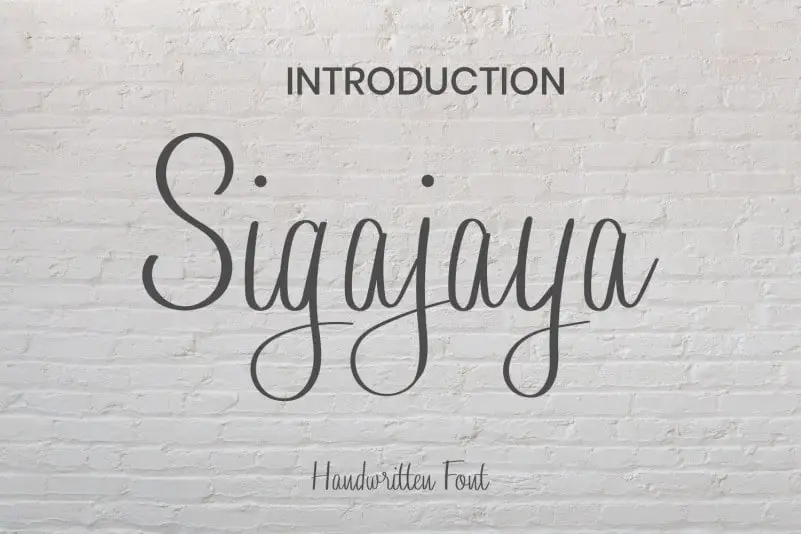
Sigajaya Handwritten Font – Download Grátis
A Sigajaya Handwritten Font é uma elegante fónta escrita a mão com um toque suave e amigável. Perfeita para aqueles desejos de criar designs alegres, essa fónta relaxada se adapta à uma ampla gama de aplicações. Seja em sua identidade visual, cartões de aniversário, postes nas redes sociais ou até mesmo seus e-mails de boas-vindas, ela é perfeitamente adaptável a esses formatos. Com sua graciosidade genuína, você pode explorar a criatividade através da design de logotipos, cartões de visita, embalagens, designs para eventos e outros. A Sigajaya Handwritten Font tem tudo que um designer precisa para criar uma identidade visual única e reconhecível, enquanto mantém aquele toque pessoal tão querido no mundo da gráfica.